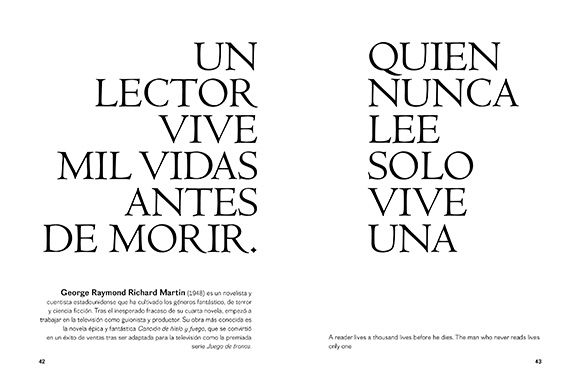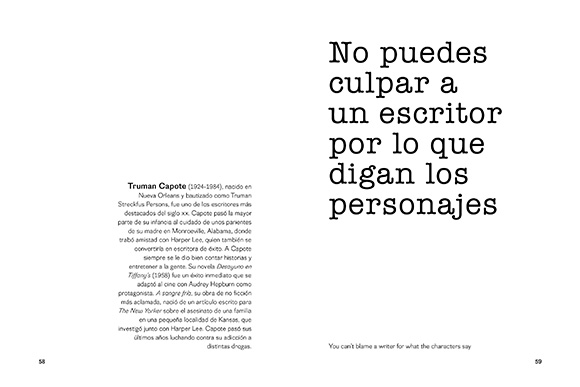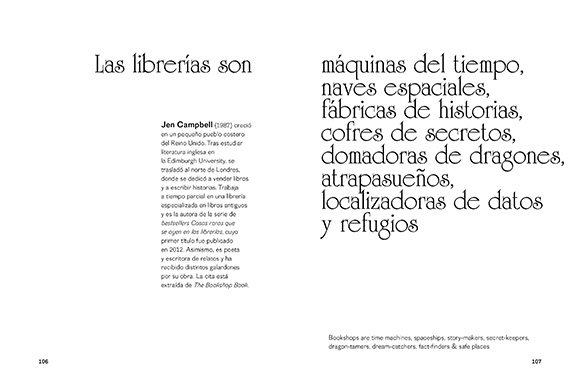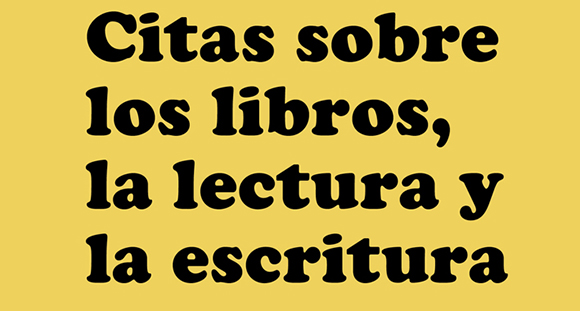
Abrí el libro Citas sobre los libros, la lectura y la escritura de Bart Van Aken por una página al azar y me encontré con esta rotunda declaración del director de cine John Waters «Si vas a casa de alguien y ves que no tiene libros, no te lo folles». Bien, me apunté el consejo y seguí navegando por las páginas del libro.
Para cada una de las citas se utiliza una tipografía diferente y la composición y selección de todas ellas las ha llevado a cabo el tipógrafo flamenco Gert Dooreman. Tengo que decir que la mezcla entre estas citas y la tipografía utilizada en las mismas multiplica el sentido del texto y enriquece notablemente el valor del volumen para todos los amantes de la letra y su expresión. Si a ello añadimos que cada puesta en página de las citas está realizada de una manera diferente estamos además ante un conjunto de expresiones gráficas del que sin duda extraer buenos ejemplos e ideas.
Me gustan las citas sobre algo ligado tan intimamente a la tipografía y como las letras interactuan con el texto. Solamente pondría un «pero» y es que yo hubiera puesto el nombre de la tipografía utilizada en la misma página en la que aparece no en una relación de todas ellas al final. Esto hubiera sido más útil para identificarlas. En cualquier caso un detalle menor para para un título muy interesante.
Citas sobre los libros, la lectura y la escritura
Bart Van Aken, Gert Dooreman